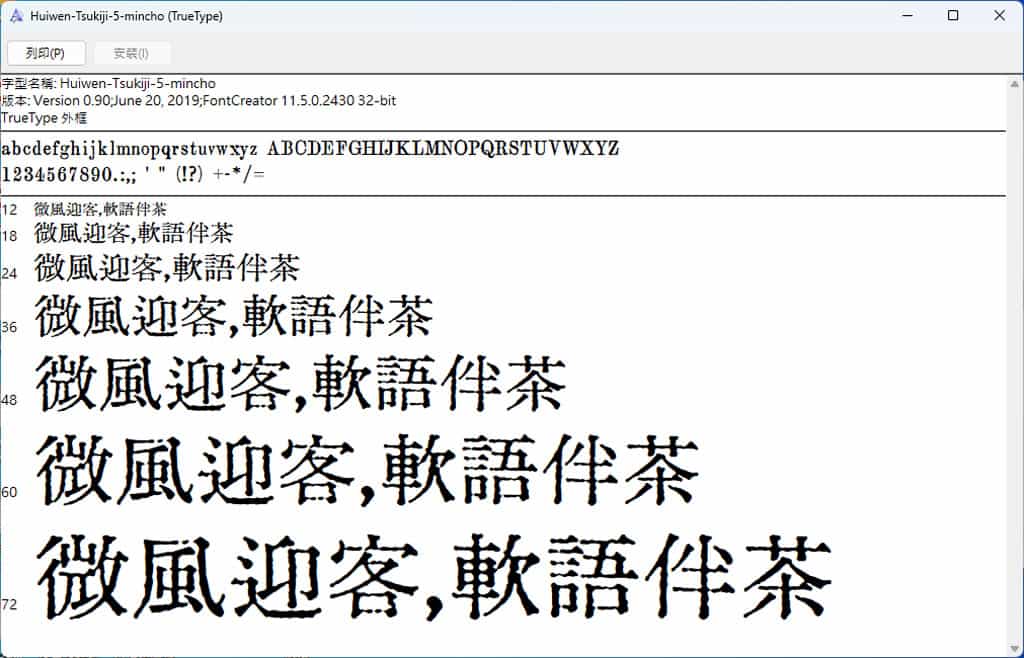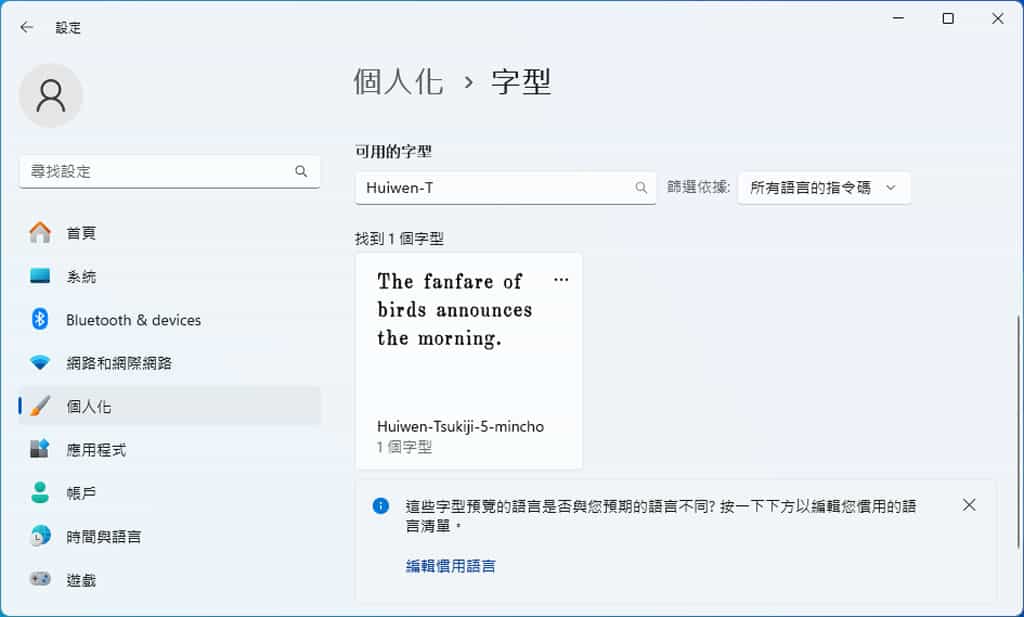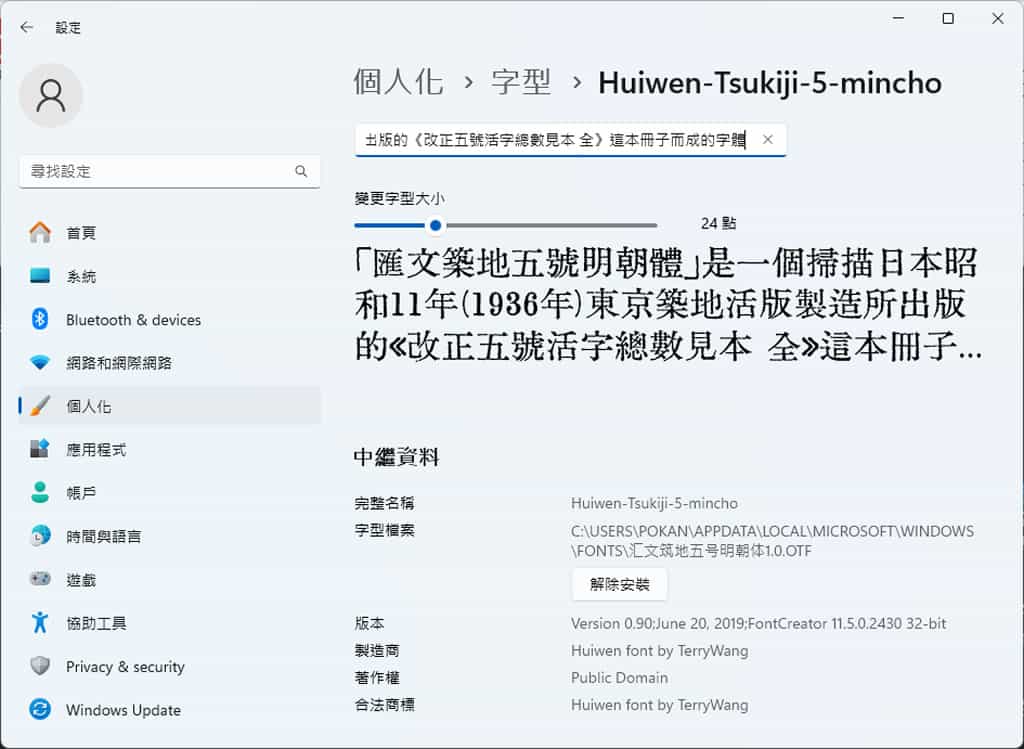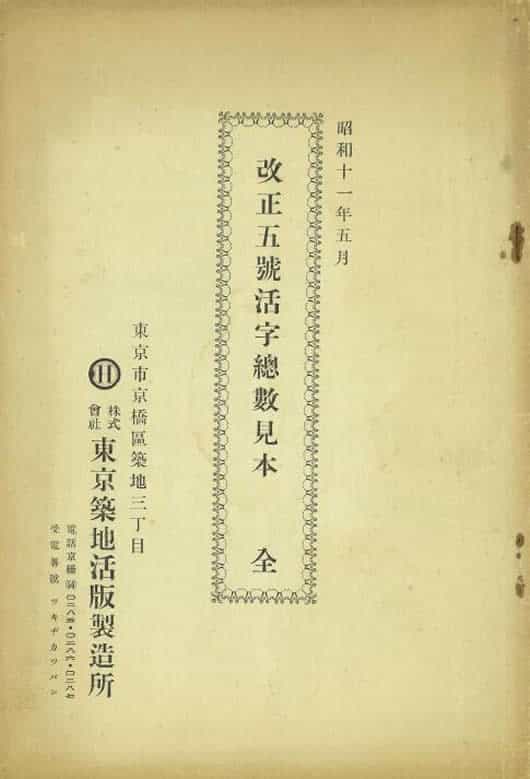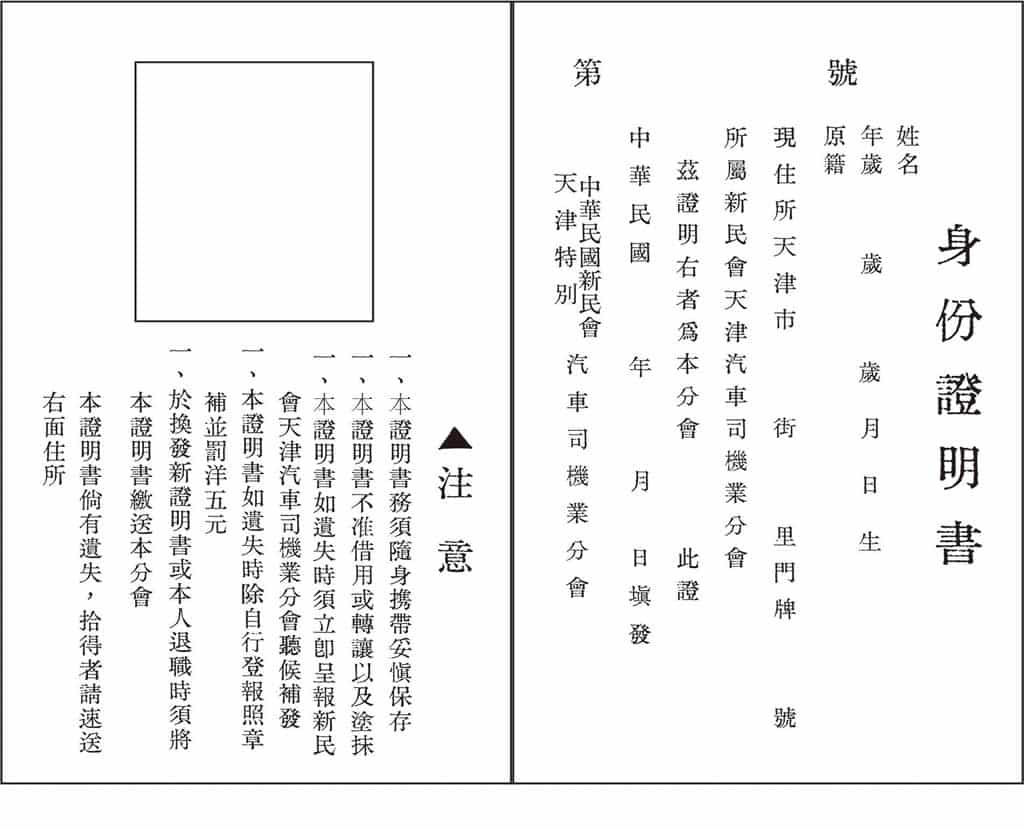
「匯文築地五號明朝體」是一個掃描日本昭和11年(1936年)東京築地活版製造所出版的《改正五號活字總數見本 全》這本冊子而成的字體,其字型是現在日本明朝體之源流和當時中國的鉛字字型一樣相似,兩者都源自於康熙字典的字型。根據作者自述,整個字型除了收錄了冊子內的字體外,還收錄所有平假名、片假名和 241個萬葉假名跟變體假名。然後補了西文字母還有一些圖形符號,共收錄 9262個字符,但未包含簡體字和日本新字型,不保證不缺字,但足以應付一般日常使用。